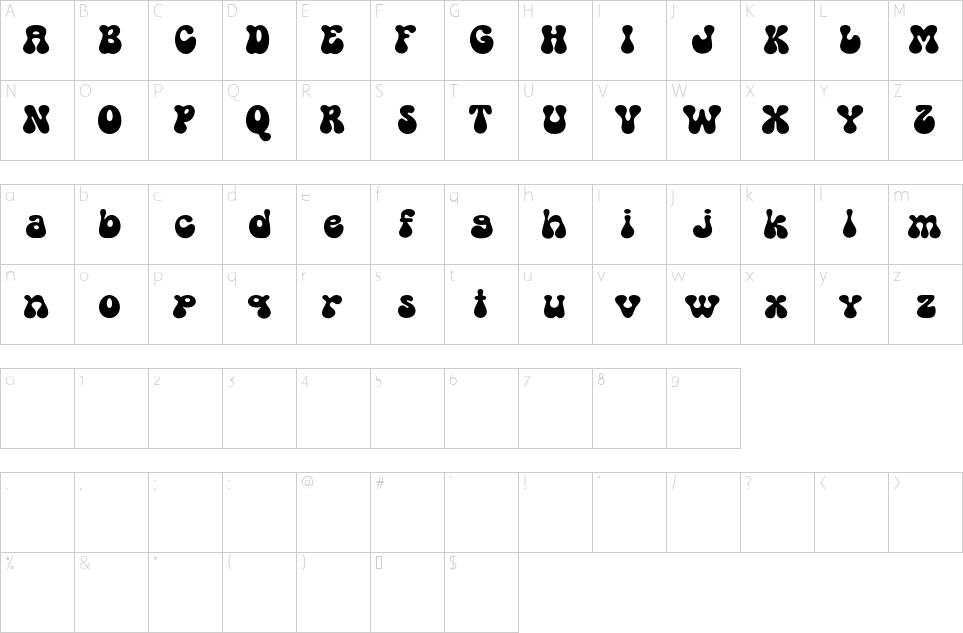
Aqui está uma descrição em português do Brasil para a página de download da fonte Gunydrops: Gunydrops é uma fonte gráfica de natureza simples e agradável, ideal para textos em sites ou blogs. Desenvolvida pelo Designer desconhecido Dharmas Studio, a fonte apresenta uma combinação harmônica de linhas e espaçamentos que ajudam a fazer os textos mais legíveis e atraentes. Com uma aparência moderna e despojada, Gunydrops é uma opção perfeita para criar uma aparência pessoal em seu design web. Suportando tanto sistemas operacionais Windows quanto Mac, é uma fonte que pode se adequar a qualquer projeto de design. Mais de quatrocentos usuários já descarregaram a fonte para suas necessidades de design, e você pode ser o próximo a fazê-lo. Descubra uma nova maneira de dar vida aos seus projetos com a Gunydrops. Descarregue já e explore as possibilidades criativas que esta fonte oferece.